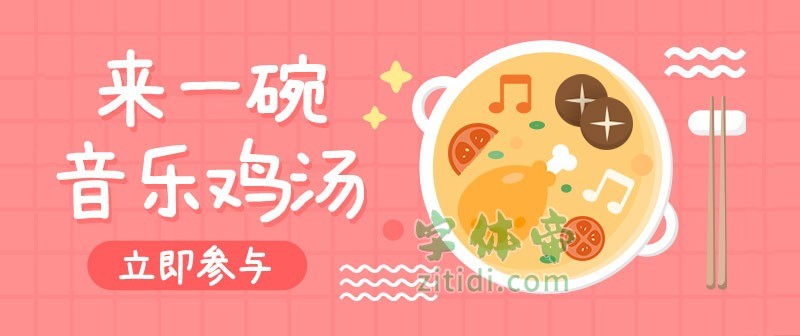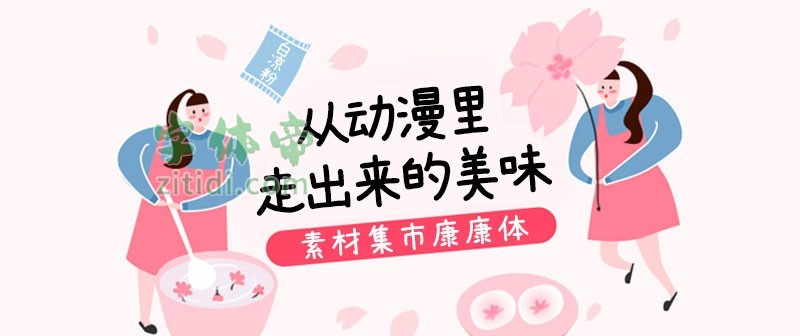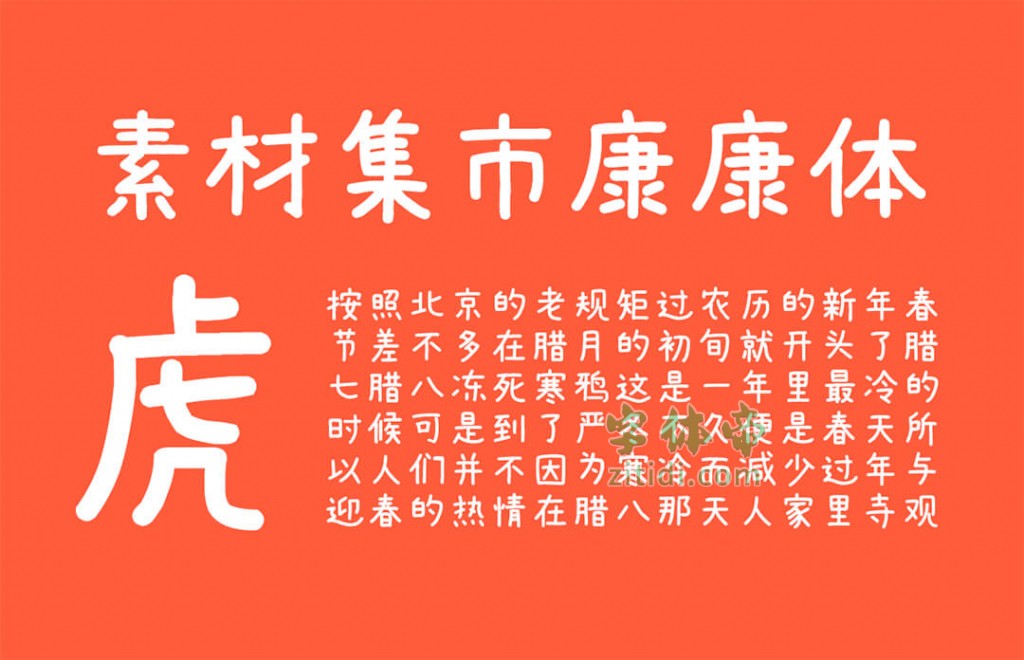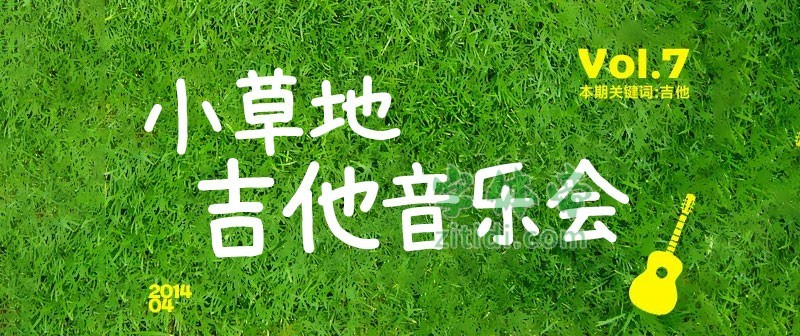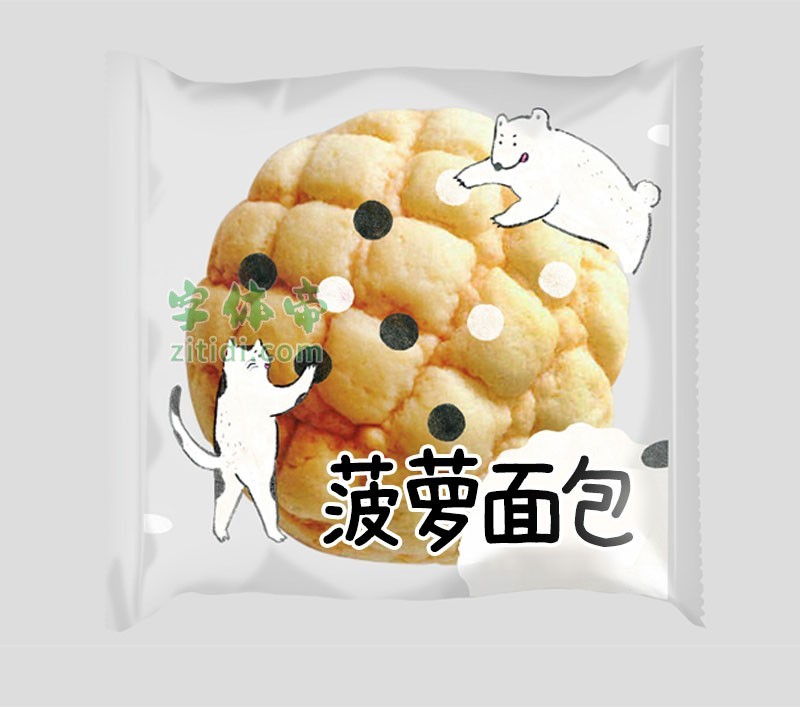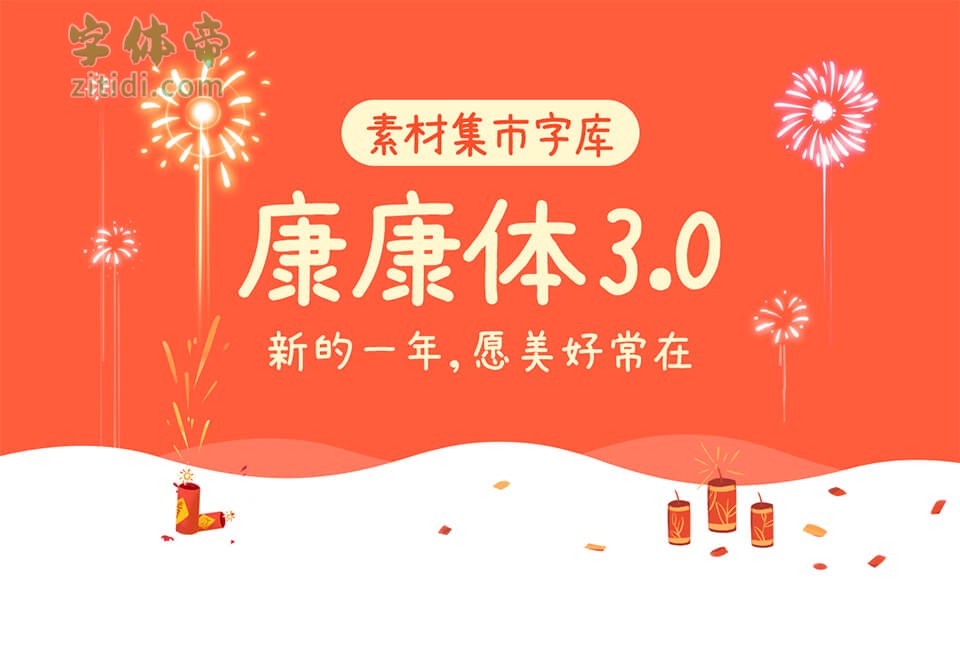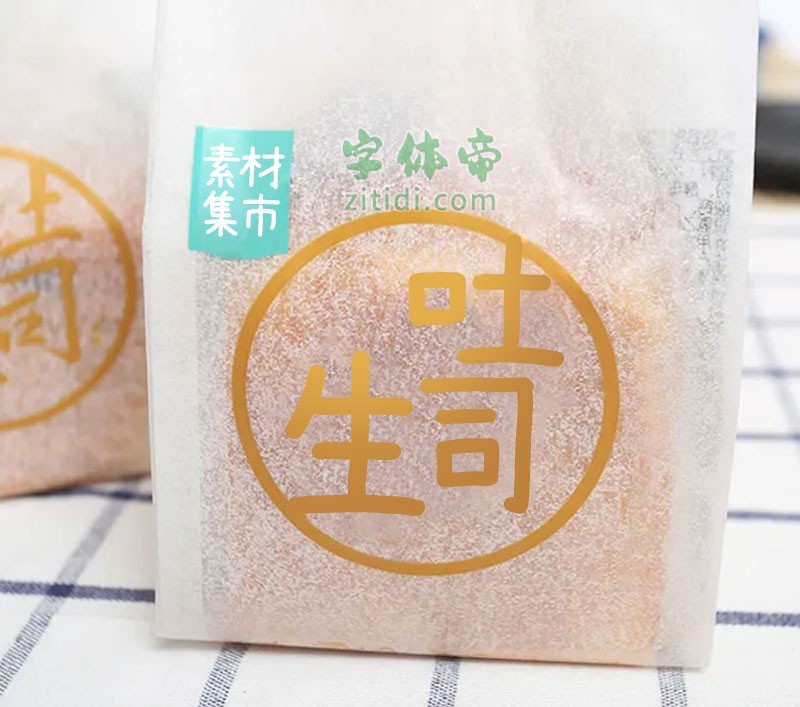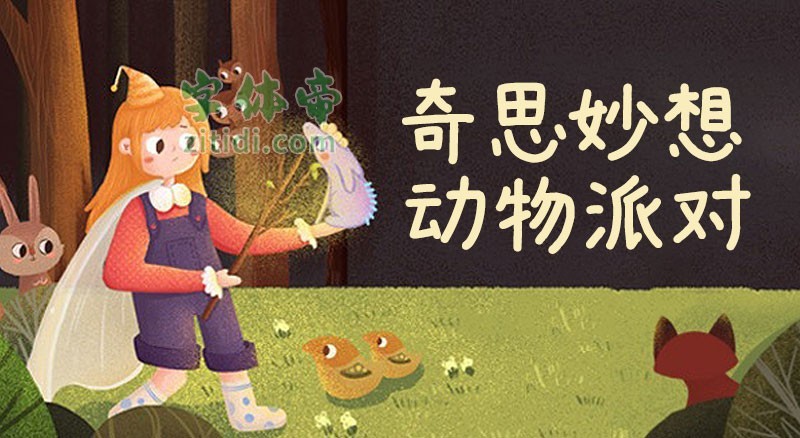
素材集市康康体是一款萌系可爱手写风格中文字体,时隔一年终于迎来更新。1.0版是在2020初疫情隔离期间完成,发布至今获得各界朋友肯定。
2.0版由字集团队成员时光羊独立完成,用了3个月时间增补3500+字,目前字库汉字和字符共计6150个,无论是个人还是企业都可以免费商用。
3.0版本由字集团队成员 时光羊 独立完成,用了近6个月时间,在1.0版基础上增加5131个字补齐GB2312-80编码字库,目前汉字和字符共计7754个。
“素材集市康康体3.0”是一款书写很新颖的字体,字体大方,适合各种设计作品使用!欢迎下载!